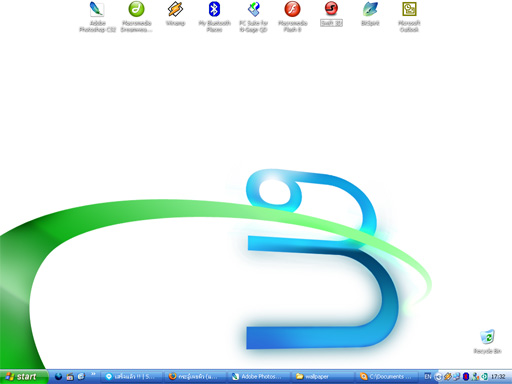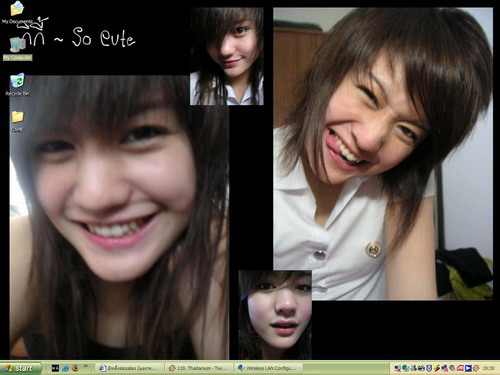
อาจเป็นเพราะสีก็ได้นะครับ  :34:
คือมันใช้หมดทั้งร้านรูป ไม่รู้จะใช้สีไรแล้วไง
(ไอ่ที่ก๊อพทำให้มันอนาจารไปหน่อย  :27:)
กรี๊ดๆๆ สามตกเขียว  :26:
ตูทำแบบทึบ ๆ แล้วมันดูสวยกว่าว่ะสาม
สามสวย :05:
มีหมาย่างแต่ดันใช้ไอ้อี :23:
:05: ก็มันหลายอัน ต้องแบ่งๆกันใช้
เธŠเธญเธšเธ›เธธเนˆเธก start :25:
มันสามารถเปลี่ยนแปลงแก้ไขได้ครับ โดยใช้โปรแกรม...